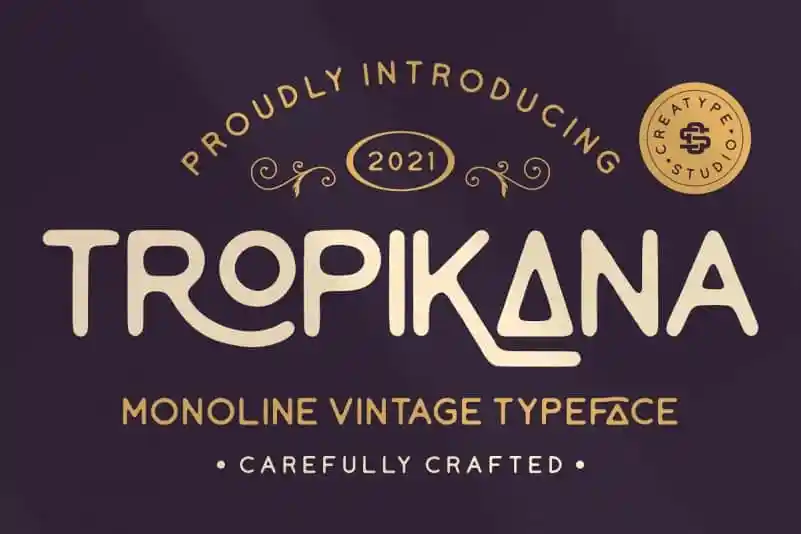
Tropikana Display Font – Download Grátis
Tropikana Display Font é uma fonte vintage criada a mão na tipografia sans serif. Esta fonte é perfeita para várias aplicações visuais, desde criar marcações e logotipos até criação de produtos e embalagens. Seu design gráfico elegante faz deste um recurso ideal tanto para ideias de moda moderna quanto para celebridades vintage ou eventos exclusivos. Com sua inspiração nos estilos do passado, Tropikana Display é perfeito para adicionar uma sensação artística às suas criações digitais. Use-a em anúncios, postagens nas redes sociais e em qualquer outro projeto que deseje dar um toque de personalidade ou originalidade. Aqui está a oportunidade de incorporar um elemento nostálgico ao seu trabalho, seja uma marca digital ou um produto de edição limitada.